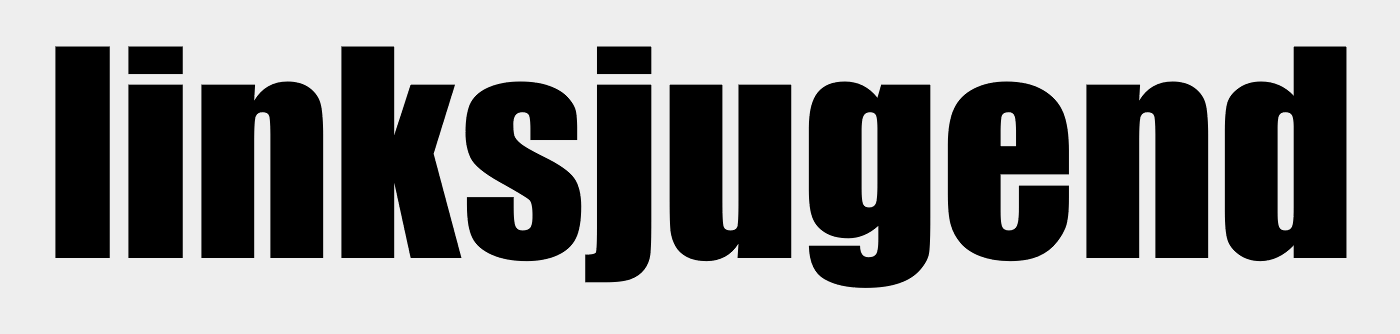
Schriftart Linkjugend solid
das ist auf ersten Blick fast eine Impact, aber e und o passen absolut nicht. Also ist es wohl eine Helvetica Inserat. Ich habe hier noch Reste von alten Wahhlkampfplakaten der Linken, damit geht das Identifizieren einfacher. Auf dem Bild sehen e und o sehr viel anders aus als auf den Plakaten der Linken.
In den Bitstreamsammlungen bei Corel-Produkten findet man die als Swiss 921.
Hier zum Vergleich die Monotype-Version der Impact:
Diese wird mit MS-Produkten und in den MS-Corefonts (frei) verbreitet.
Ich tippe dem Bild nach eher auf die Swiss 921 BT als eine echte Helvetica Inserat.